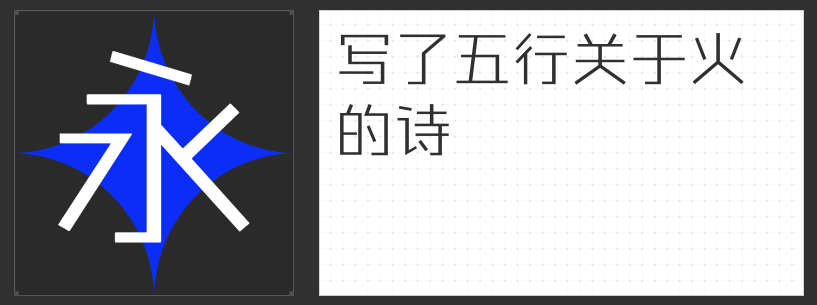
四款创意字体:为短视频注入视觉灵魂的“魔法笔触”
在短视频设计的竞技场中,字体早已突破“文字载体”的单一功能,成为传递情绪、塑造风格、引导观众注意力的核心视觉元素。以下四款各具颠覆性的创意字体,以独特的笔画语言与结构美学,为短视频创作打开新的想象空间。
一、字恋狂风摇简 粗体
这款字体以“反常规”为设计内核,故意放大的失衡比例与摇曳的笔画轨迹,仿佛被春风拂乱的信笺,在动态画面中自带呼吸感。歪扭的线条中藏着孩童涂鸦的天真,粗细不一的笔触却暗含书写者的笃定,特别适合作为情感类短视频的标题或手账式字幕,用“不完美”的温暖质感打破机械感的冰冷,让文字成为传递情绪的视觉载体。
二、励字钧线黑简 细体
全直线设计的几何美学在此达到极致,精准的斜度与利落的转折构成视觉节奏,如同用尺规绘制的未来符号。这款字体摒弃所有冗余装饰,以极简线条重构文字骨架,却在转折处暗藏东方书法的顿挫韵律,既降低阅读疲劳,又以独特的个性感成为画面焦点。适合科技、知识类短视频的标题设计,用冷静的理性美平衡画面的情绪表达。
三、励字超级勇士简 微粗
作为通用黑体的进化形态,这款字体在方正结构中融入圆润拐角,如同在钢筋森林中开辟出一片柔软绿洲。适度的外圆角设计既保留黑体的稳重感,又为屏幕显示注入呼吸感,特别适合作为长段文字的载体。无论是知识科普还是故事叙述,都能以清晰舒适的视觉体验留住观众目光,在“稳”与“灵”的平衡中提升内容专业度。
四、励字跨界黑简 超级黑
90%字面率与夸张的笔画粗度构建出强烈的视觉冲击力,微抬的曲线钩画却如乐符般打破沉闷。这款字体将直线与曲线进行戏剧化碰撞,在厚重块面中暗藏灵动韵律,特别适合作为短视频的黄金三秒标题。无论是运动励志还是时尚潮流主题,都能以极具张力的视觉语言瞬间抓住观众注意力,让标题成为画面的“视觉钩子”。
当短视频设计需要突破常规表达,这四款字体将以颠覆性的创意语言,为内容注入鲜活的视觉灵魂。